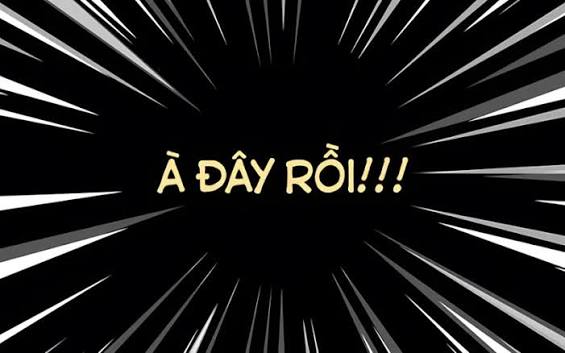
Tải 5+ bộ Font MTO Astro City Việt hoá sắc nét cho thiết kế Manga
Designer khi làm truyện tranh thường gặp lỗi khi sử dụng font MTO Astro City do mất dấu tiếng Việt hoặc các nét nghiêng bị răng cưa khi đưa vào in ấn. Những lỗi hiển thị này làm giảm tính thẩm mỹ của thiết kế, đồng thời khiến quá trình chỉnh sửa từng ký tự mất nhiều thời gian.
Font MTO Astro City là gì?
MTO Astro City là một trong những phông chữ tiêu biểu thuộc dòng MTO font Việt hóa, được thiết kế chuyên biệt cho việc trình bày lời thoại và hiệu ứng âm thanh (SFX) trong truyện tranh. Đặc trưng của bộ chữ này là cấu trúc hình học hiện đại, mang hơi hướng công nghệ. Với các nét chữ dứt khoát, Astro City tạo nên cảm giác năng động, phù hợp cho các dự án game, poster hành động hoặc bao bì sản phẩm dành cho giới trẻ.
Bộ font này cung cấp đầy đủ các biến thể từ nét thẳng đứng đến font mto astro city italic (nghiêng). Bản Font MTO Astro City Việt hoá tại In Viva đã được xử lý kỹ lưỡng hệ thống dấu thanh tiếng Việt, đảm bảo các ký tự có dấu không bị chồng lấp. Việc ứng dụng font việt hóa manga mto astro city giúp các ấn phẩm quà tặng và bao bì của doanh nghiệp giữ được phong cách nghệ thuật nguyên bản mà vẫn đảm bảo tính thẩm mỹ ngôn ngữ.
Font MTO Astro City đẹp 01
Lưu ý: Khi sử dụng font mto astro city italic, designer nên chú ý khoảng cách giữa các từ để đảm bảo tính dễ đọc khi in trên các bề mặt cong như bình nước hay ly sứ.
5 ứng dụng của font MTO Astro City trong thiết kế và in ấn
Vẻ đẹp mạnh mẽ và cá tính của MTO Astro City giúp các sản phẩm bao bì, quà tặng doanh nghiệp trở nên nổi bật hơn khi kết hợp cùng các kỹ thuật in ấn và gia công phù hợp:
• Thiết kế bao bì đồ chơi và sản phẩm công nghệ: MTO Astro City phù hợp để thể hiện tên thương hiệu, tên sản phẩm trên hộp giấy, hộp cứng nhờ kiểu chữ mang phong cách hiện đại, tạo cảm giác năng động cho các dòng sản phẩm hướng đến giới trẻ.
• Sản xuất set quà tặng sự kiện game và công nghệ: Logo sử dụng font MTO Astro City khi in UV trên sạc dự phòng, loa bluetooth hoặc phụ kiện điện tử giúp món quà có điểm nhấn cá tính, phù hợp với các chương trình quảng bá thương hiệu.
• In ấn poster, banner và ấn phẩm truyền thông: Với kiểu chữ mang hơi hướng truyện tranh, font Astro City phù hợp để trình bày tiêu đề, slogan ngắn trên poster, backdrop sự kiện hoặc các thiết kế quảng cáo dành cho khách hàng trẻ.
• Trang trí túi giấy thương hiệu phong cách hiện đại: Sử dụng MTO Astro City trên túi giấy Ivory hoặc giấy mỹ thuật giúp bộ nhận diện thương hiệu thể hiện nét sáng tạo, phù hợp với các sản phẩm giải trí, thời trang và công nghệ.
• Sản xuất tem nhãn decal dán sản phẩm: Các thông tin ngắn như tên bộ sưu tập, mã sản phẩm hoặc slogan khi sử dụng font Astro City có thể tạo điểm nhấn trên tem nhãn, giúp sản phẩm dễ nhận diện hơn.
Font MTO Astro City đẹp 02
4 lưu ý khi sử dụng font MTO Astro City Việt hóa
Để font MTO Astro City giữ được vẻ đẹp khi chuyển từ bản thiết kế sang sản phẩm thực tế, designer cần chú ý các yếu tố kỹ thuật sau:
• Kiểm soát độ nghiêng của ký tự: Phiên bản nghiêng (Italic) của Astro City có các góc chữ đặc trưng. Khi thiết kế logo hoặc tem nhãn kích thước nhỏ, nên kiểm tra khoảng cách giữa ký tự và dấu tiếng Việt để hạn chế tình trạng dính nét khi in.
• Tối ưu đường Path cho gia công bế nổi: Khi sử dụng MTO Astro City làm logo trên hộp quà, file vector cần được xử lý các điểm neo và đường cong phù hợp. Việc tối ưu path giúp khuôn dập tái hiện rõ hình dáng chữ, hạn chế ảnh hưởng đến phần giấy trong quá trình gia công.
• Lựa chọn màu sắc phù hợp với phong cách thiết kế: Font Astro City phù hợp với các bảng màu có độ tương phản như xanh đậm, cam, đỏ hoặc các tông màu nổi bật. Designer nên kiểm tra màu CMYK trước khi in để hạn chế sai lệch màu trên thành phẩm.
• Hạn chế sử dụng cho nội dung dài: Đây là kiểu chữ thiên về tiêu đề và điểm nhấn. Với các đoạn mô tả sản phẩm hoặc thông tin chi tiết, nên kết hợp cùng font Sans-serif dễ đọc để bố cục cân đối hơn.